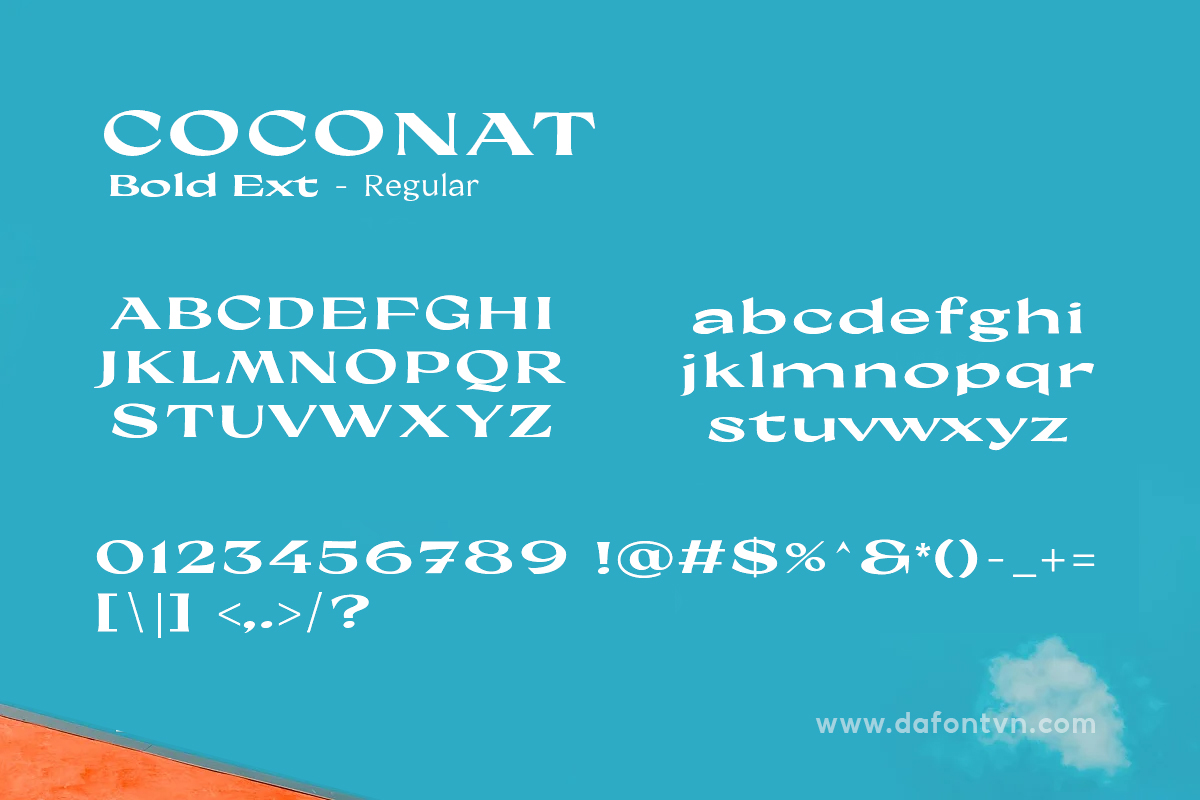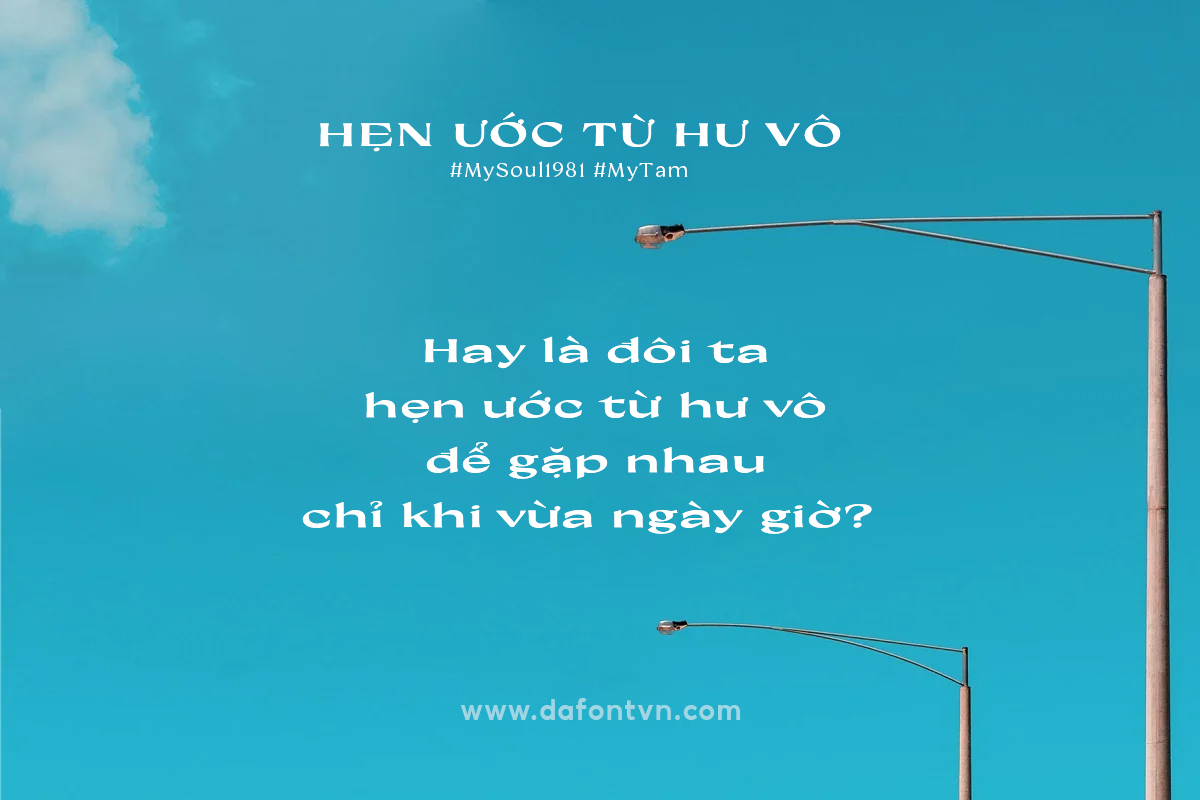
Font Việt Hóa Coconat (đầy đủ 2 font)
Coconat font được lấy cảm ứng từ những chữ cái vẽ không thay đổi mang phong cách hiện đại phù hợp cho rất nhiều các thiết kế khác nhau. Font được Việt hóa đầy đủ 2 kiểu Coconat BoldExt và Regular, ngoài ra font kerning, tối ưu và chỉnh sửa lại một số chỗ so với font gốc để phù hợp với các dấu tiếng Việt.